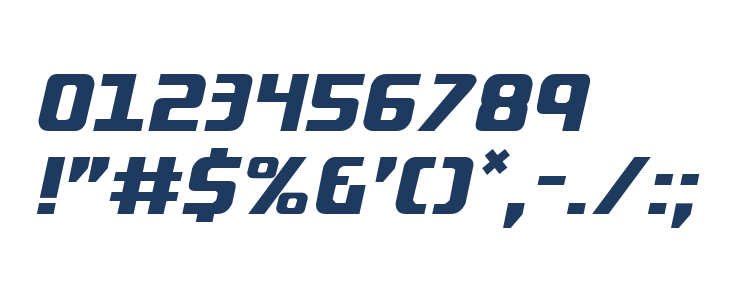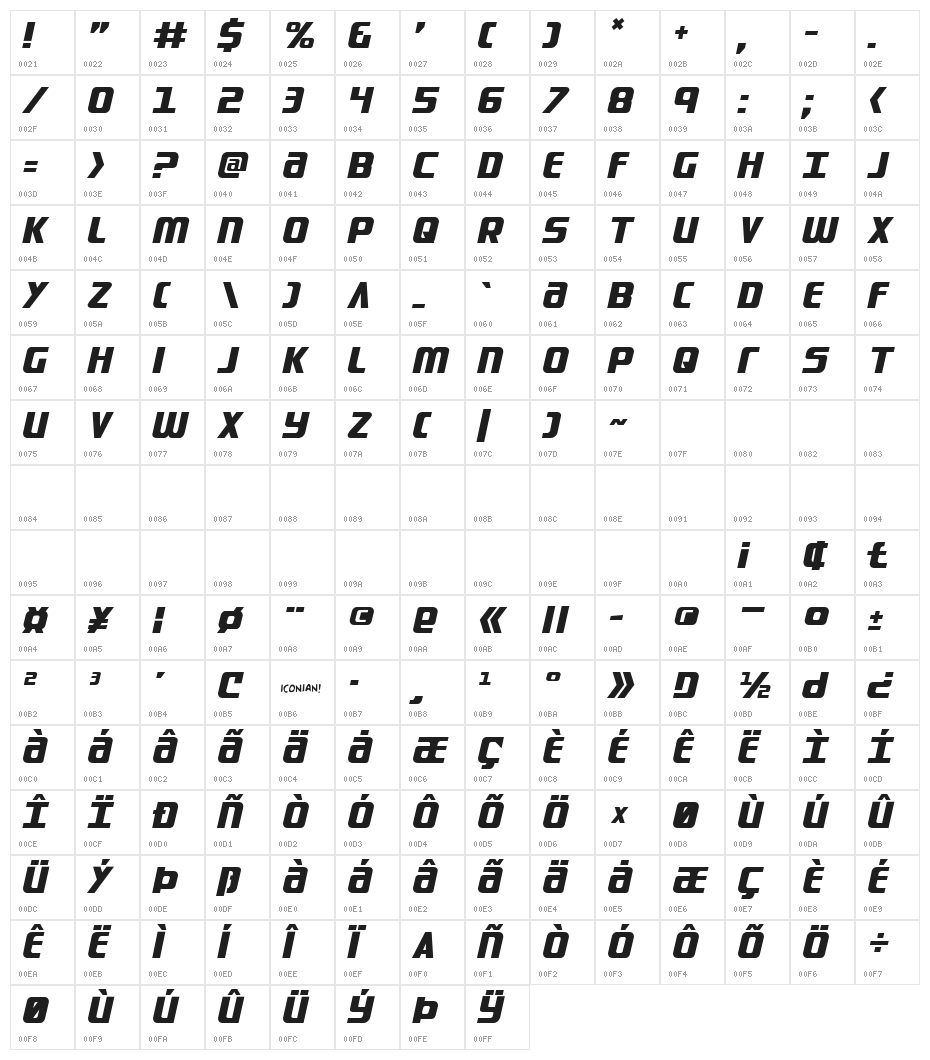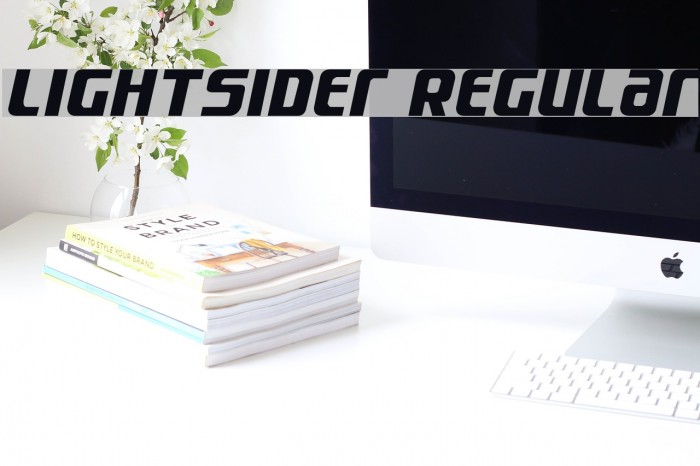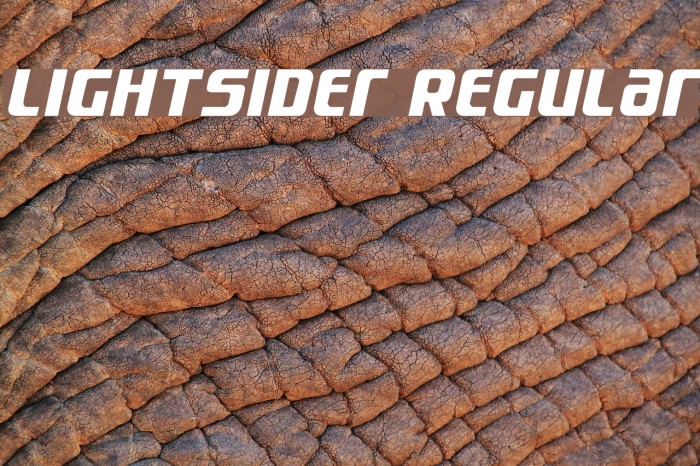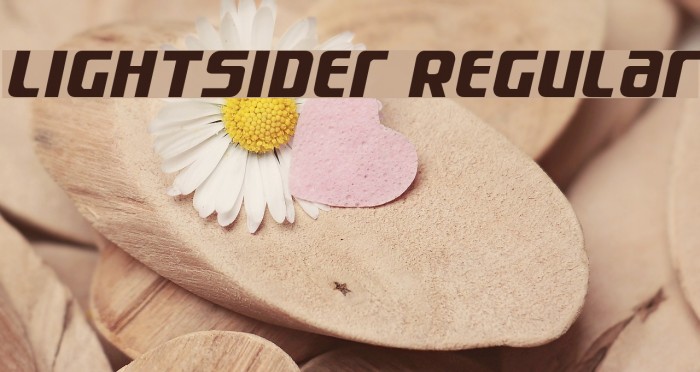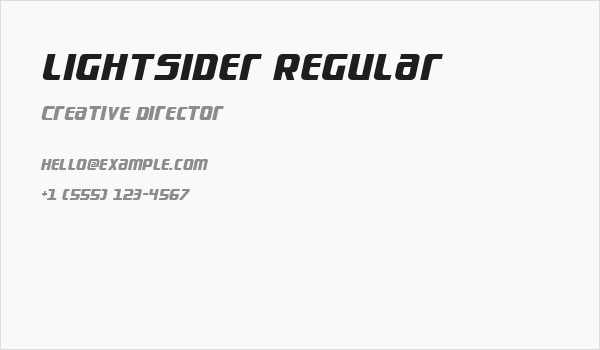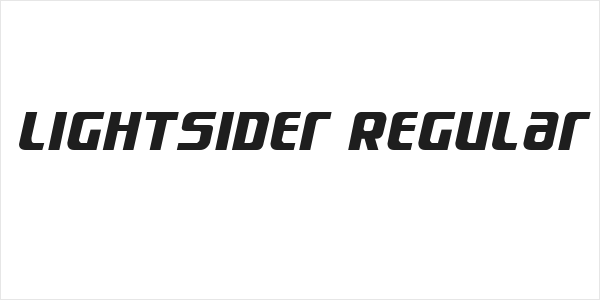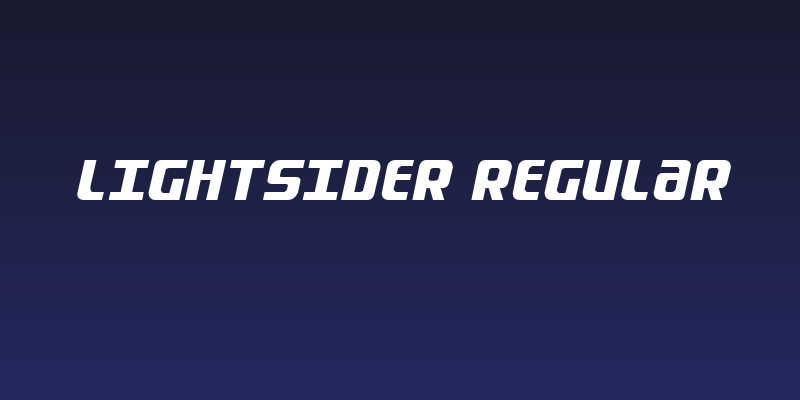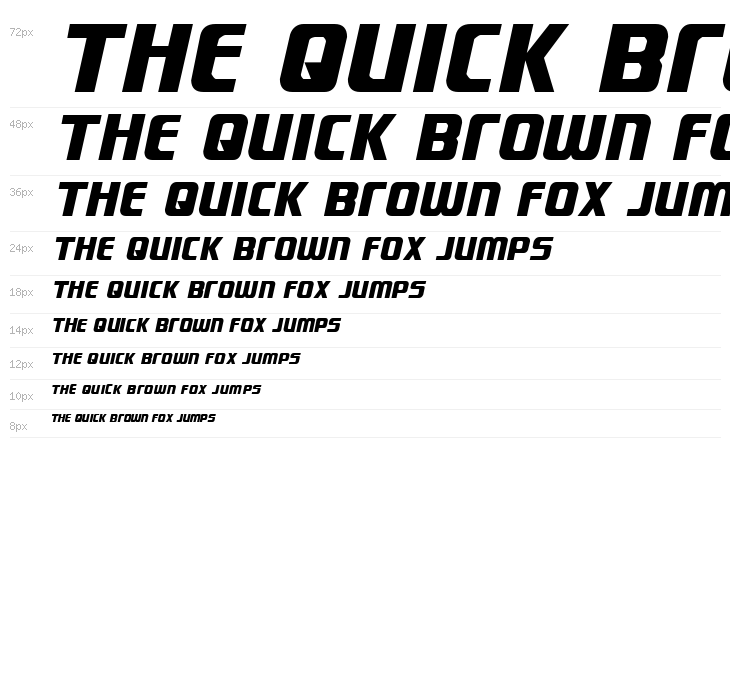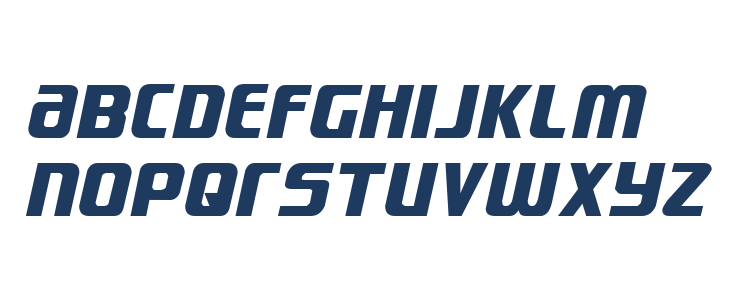
Lightsider Regular Font
| Progetti proposti | Ideal for technology branding, sports team logos, video game titles, and sci-fi themed designs. |
Lightsider Regular